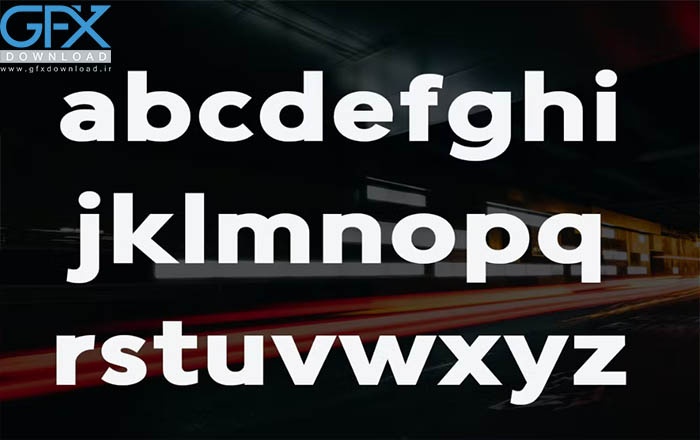
فونت مسابقه ای Pulse
دانلود رایگان فونت مسابقه ای Pulse یک فونت انگلیسی و رایگان زیبا پر رنگ و جسورانه. Pulse یک فونت مسابقه ای است که جسارت و سرعت را نشان می دهد. فونت پالس همه کاره است و برای هر طرحی از جمله لوگوها، آگهی ها، پوسترها، تیترها، ورزش، ویرایش ویدئو و موارد دیگر بسیار مناسب است. امکانات آن بی پایان هست.
فونت انگیسی مسابقه ای Pulse
فونت مسابقه ای Pulse - Bold Racing برای اهداف طراحی قالب، بروشور، ویدئو، برندسازی تبلیغاتی، لوگو و موارد دیگر بسیار مناسب است.